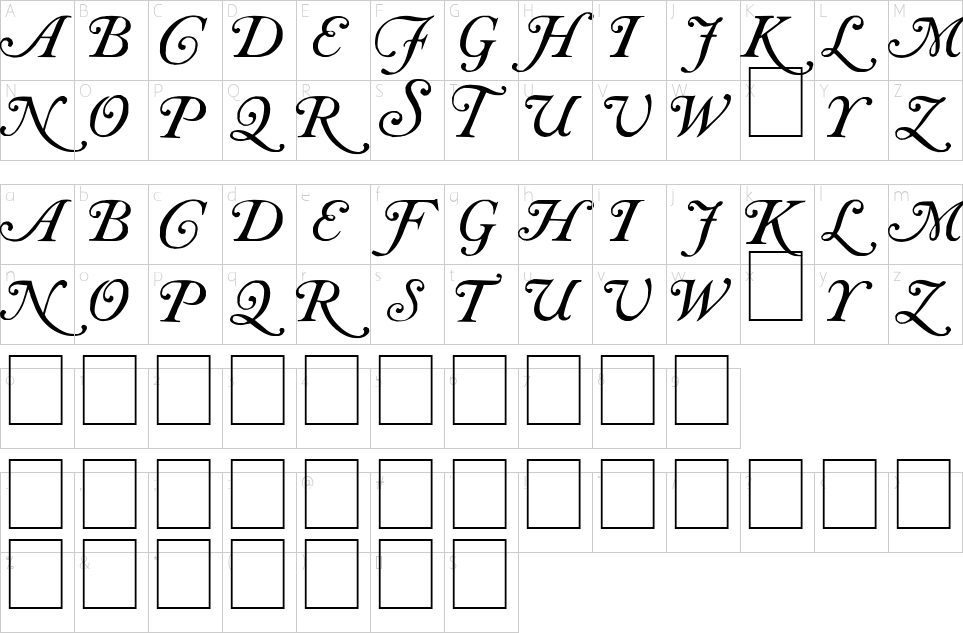
Descubra a elegância inovadora do Caslon Initials Font para seu próximo projeto gráfico! Desenvolvida por Paul Lloyd, esta fonte inicial foi projetada para oferecer uma graça e um refinamento únicos que podem transformar qualquer layout digital ou impresso. Com 6,508 downloads, você pode estar entre os muitos designers que encontraram neste design a perfeição ideal para destacar seus textos de entrada ou incorporar um toque único em suas páginas web. Caslon Initials é a escolha perfeita para quem procura uma fonte única e sofisticada que se destaca no meio do seu trabalho, criando um impacto visual imediato. Experimente já sua própria versão da fonte e veja como ela pode transformar seus projetos.